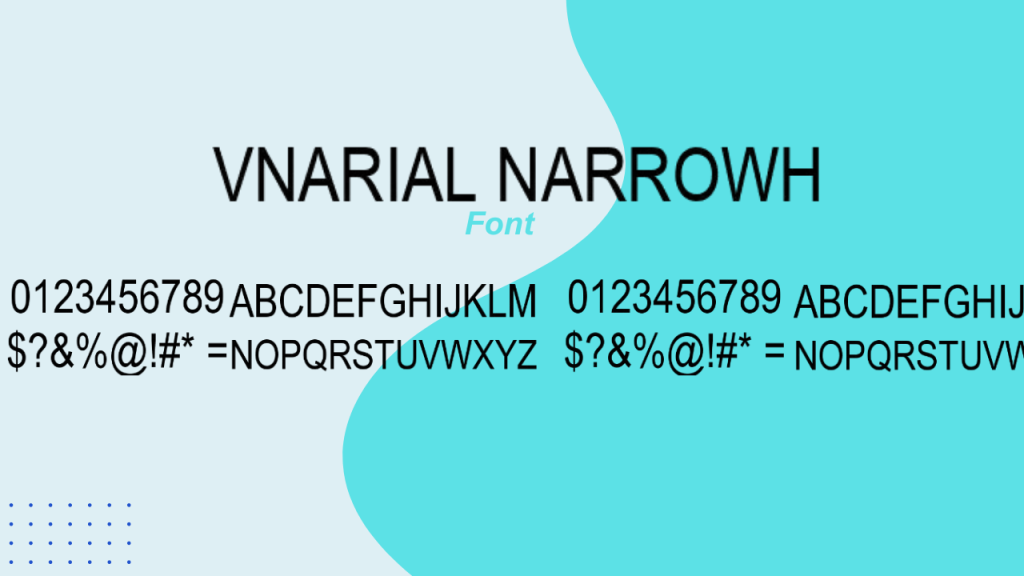
Tải Font Vnarial Narrowh
Bộ Font: Font Vnarial
Font Vnarial Narrowh là một lựa chọn tuyệt vời cho những ai đang tìm kiếm một kiểu chữ đơn giản, dễ đọc và mang tính thẩm mỹ cao. Font chữ này thường được sử dụng trong thiết kế đồ họa, quảng cáo và các tài liệu in ấn chuyên nghiệp nhờ vào đường nét thanh mảnh và không gian hẹp giữa các ký tự. Với khả năng hiển thị rõ ràng trên nhiều loại màn hình và định dạng in khác nhau, Font Vnarial Narrowh thuộc bộ font chữ không chân không chỉ phù hợp cho các bài thuyết trình mà còn lý tưởng cho việc tạo điểm nhấn trong các thiết kế sáng tạo.